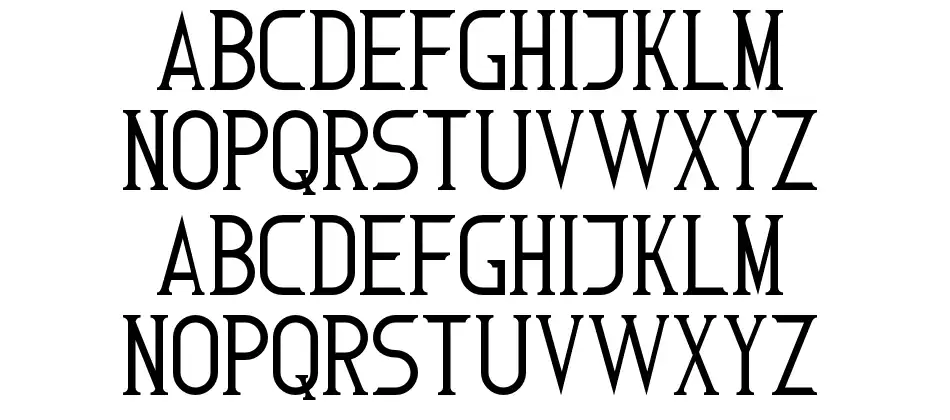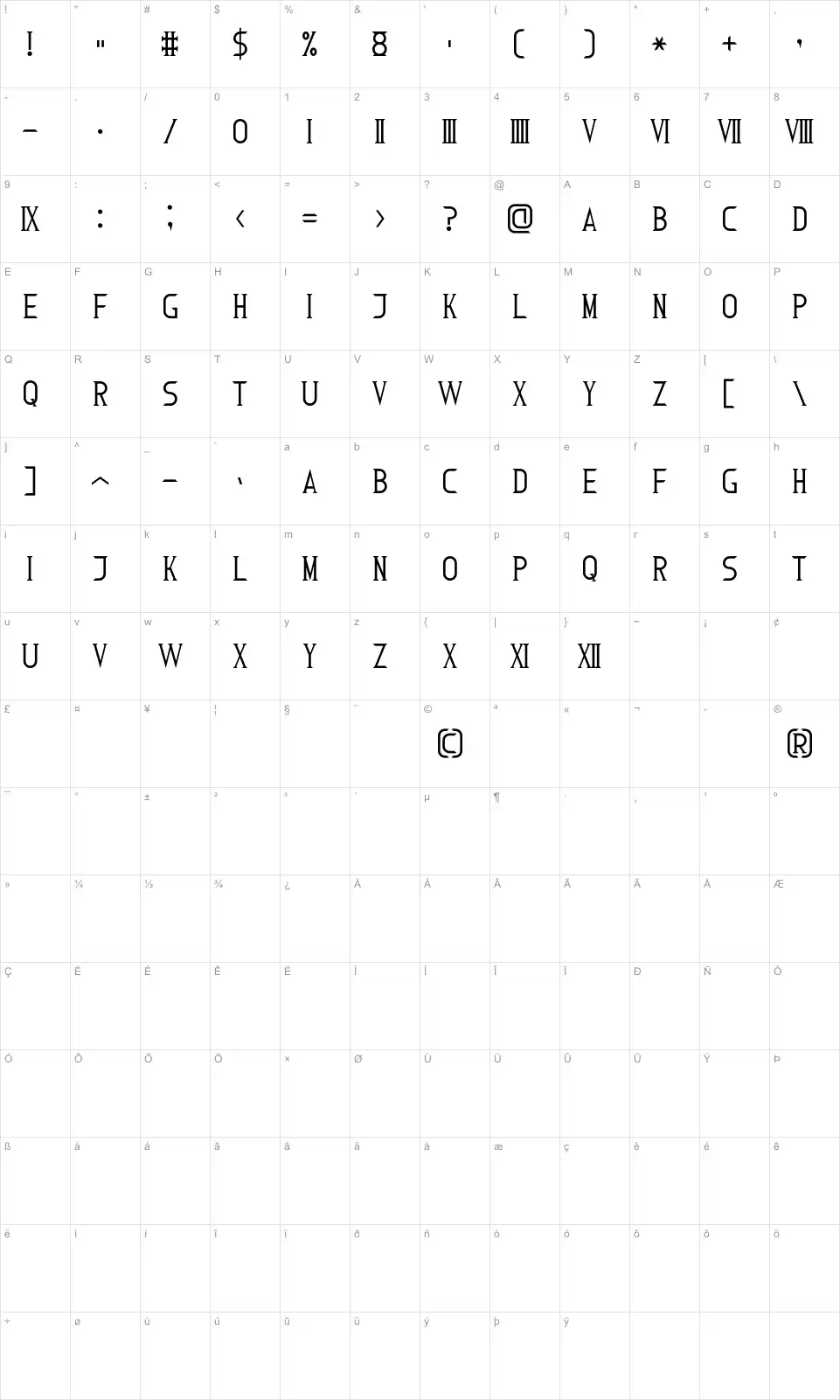
Se está à procura da fonte Roman Font 7 criada pelo designer Style-7, agora é a hora de descobrir sua beleza única. Esta fonte pertence à categoria Foreign Look e se destaca pelo estilo Roman e grego. Ela é gratuita para uso pessoal e vem em formato TTF, permitindo que você a personalize e experimente antes de começar a usar em projetos. Desde sua adição em julho de 2022, o designer Style-7 já ganhou a confiança de mais de 25837 usuários ao redor do mundo, com seu design elegante e sofisticado. Com um tamanho compacto de 78 KB, esta fonte é uma ótima escolha para quem busca algo moderno e versátil para seus projetos. Visite o site do designer para explorar mais de seu catálogo de fontes.